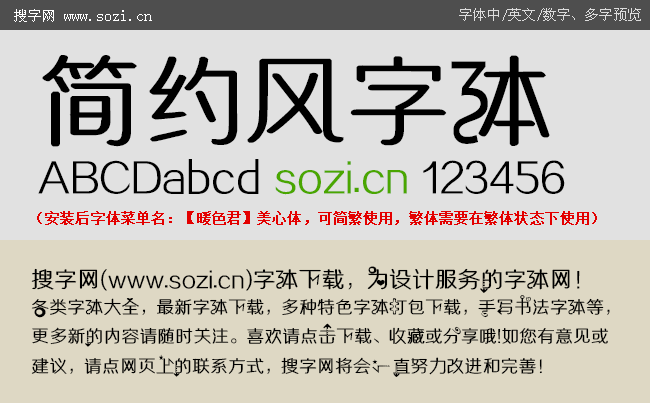
簡約風字體
搜字網(wǎng)給大家提供一款簡約風字體字體字體手機中文字體下載。這款手機字體是以正黑字體為原形。正黑體取傳統(tǒng)黑體結(jié)構(gòu),筆形全部采用平行、垂直與弧度的流線形設(shè)計,簡潔易識、美觀大方,具有個性,加之鏡像對稱的現(xiàn)代構(gòu)成形式,達到莊重與簡潔有機融合、設(shè)計感與閱讀功能兼?zhèn)涞淖罱K效果。加入卡通裝飾后看上去非常可愛,趣味實足。特別適合喜歡卡通的朋友在手機上安裝使用。